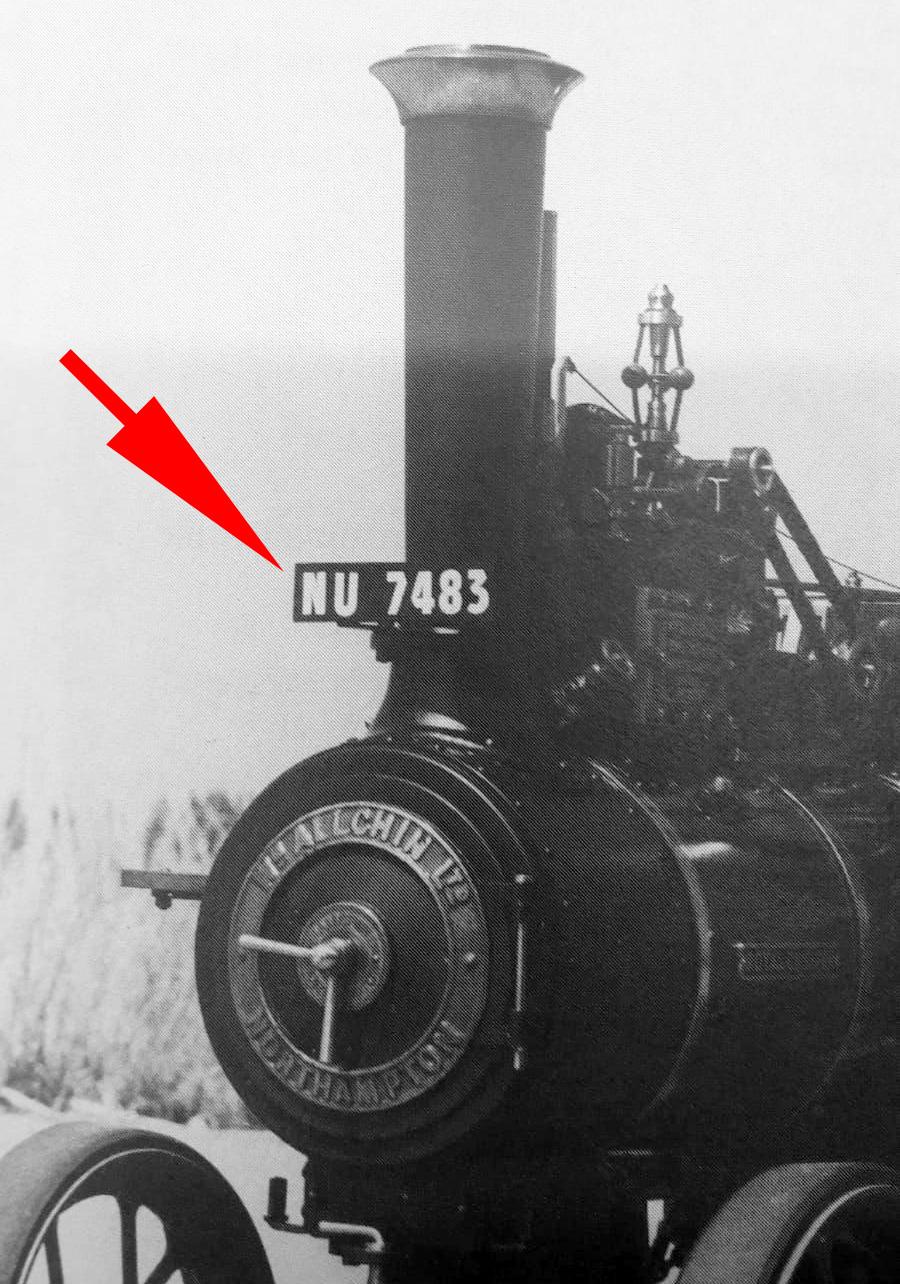
Suche Schriftart von einem Nummernschild (Dampftraktor)
Hallo Ich suche eine ähnliche Schriftart von einem Nummernschild von diesem alten englischen Dampftraktors, das Baujahr des Traktors war ca. 1920 . Die Schriftart kann auch was kosten. Vielen Dank für Eure Mühe im Voraus.
Der Zeitpunkt ist etwas ungünstig. Vor einigen Jahren hättest Du  bei den BFG ( British Forces in Germany ) sicher tolle Unterstützung finden können. Die Schrift hat  nach meinem Dafürhalten sehr viel Ähnlichkeit mit der auf den
Kfz-Kennzeichen der  BFG verwendeten.  (War zunächst nur für die hier stationierten Kräfte gedacht, wurde aber später,-- Mitte der siebziger Jahre -- für die ganze  British Army  übernommen.)
Die beste Auskunft wirst Du aber bei  Zulassungsstellen in England  erhalten  können. Bei dem Traditionsbewußtsein der Briten ist es sogar wahrscheinlich, daß Du dort ein  Kennzeichen in Originalausführung erwerben kannst.
Britain army plate font for vehicle  in der bilder suche eingeben.
mal hier probieren. wenn die das haben kann ich für dich dort mal vorbeifahren abholen und nachbauen. Für welches Projekt ist es gedacht?
Es gibt ja sicher noch Veteranen ob die aber noch alle leben weiss ich nicht.
ich könnte einen kumpel in Wales mal fragen aber sicher bin ich nicht ob er was weiss da er nie gedient hat.
Nummernschild von diesem alten englischen Dampftraktors, das Baujahr des Traktors war ca. 1920
Das kann eigentlich kein Nummernschild sein, wenn ich der Geschichte der Kennzeichen Glauben schenken darf:
Während hier https://www.platehunter.com/news/a-guide-into-the-history-of-uk-number-plates/292 geschrieben wird, dass 2 Buchstaben und bis 4 Nummern verwendet wurden, könnte demnach doch zutreffen.
Kennzeichen wurden seit dem Motor Car Act 1903 für Pkw und Motorräder jeweils gleich ausgegeben, es kam also vor, dass ein Auto die selbe Nummer wie ein Mopped hatte. Ob Dampftraktoren Kennzeichen hatten?
Eine Google-Bildersuche nach NU7483 führt zu immer dem selben Dampftraktor, das spricht dafür, dass mittlerweile ein neues Kennzeichen angefertigt wurde, dieser hier hat die Serien- oder Typennummer 3251.
Allchin 3251, Royal Chester - the engine that launched a thousand models. Displayed on Allchin's stand at the Royal Show in Chester, 1925 and sold to J G & B Ernshaw of Gleadless nr Derby. Seen here when it was last sold in September 2011 by Cheffins for £114k + the usual added extra's.
Andere baugleiche haben ihr Kennzeichen an der gleichen Stelle montiert.